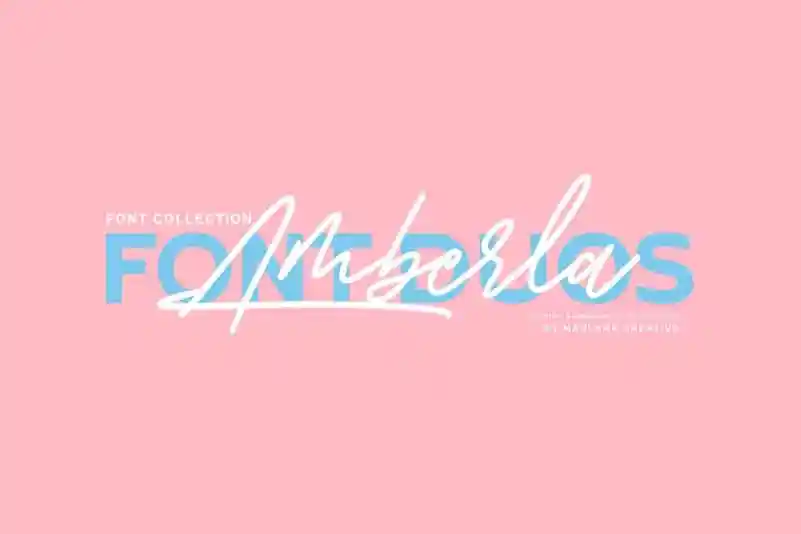
Amberla Signature Font – Download Grátis
Olá, amigos. Estamos ansiosos para apresentar à vocês a “Amberla Signature Font”, uma dupla elegante com fontes serif e sans-serif criada pelo designer Maulana Creative. Esta combinação de tipos é composta por um elegante traço script e uma mão-dura fonte de cauda, ambas escritas na própria mão. A característica mais chamativa desta dupla é sua contraste intenso e naturalidade. Proporciona um toque autêntico ao design que vem diretamente da caneta. Ideal para assinaturas, papéis de presente, logotipos, citações de tipo, capas de revistas ou livros, cabeçalhos de sites, panfletos, roupas, embalagens e identidade visual. Com o “Amberla Signature Font”, você pode trazer vida e autenticidade a seus projetos. Seja qual seja o seu projeto gráfico, este duplo tipo de fontes será uma escolha sólida para qualquer aplicação. Tornarão suas criações não apenas únicas, mas também verdadeiramente inovadoras e personalizadas.